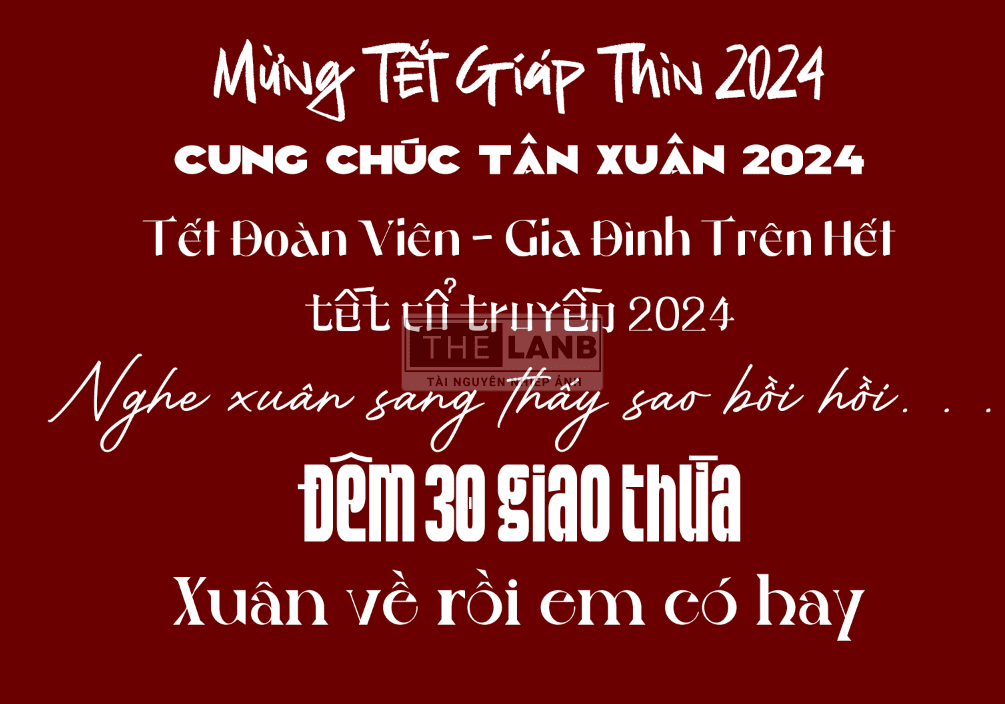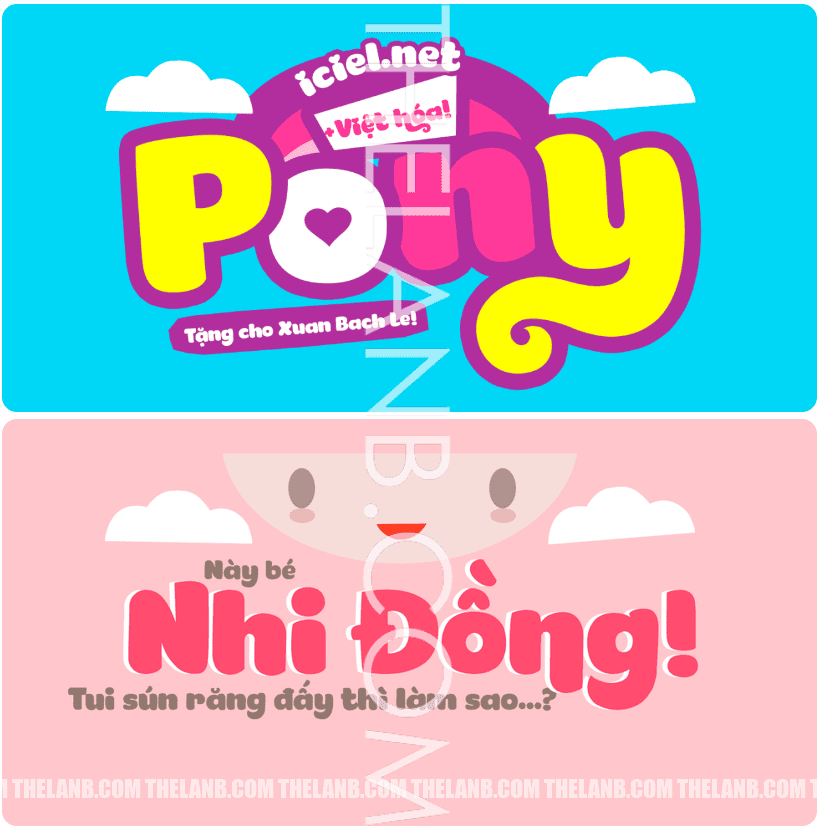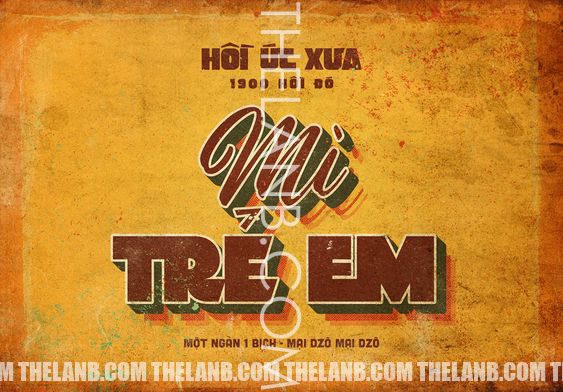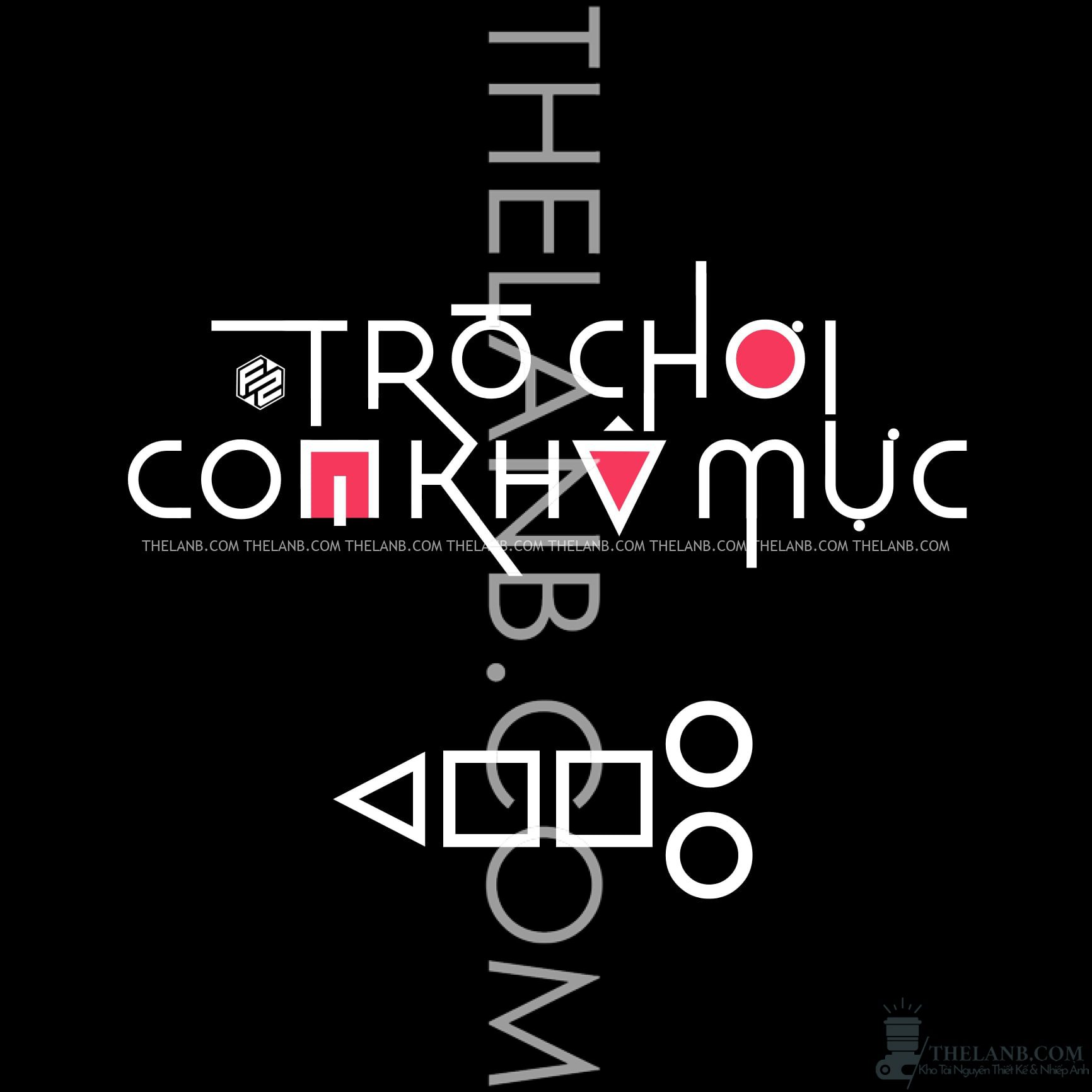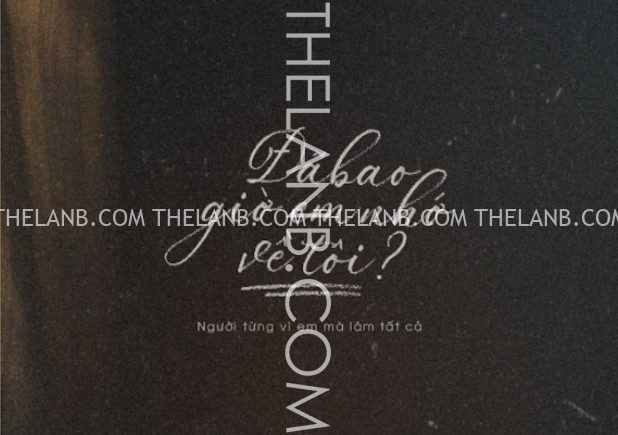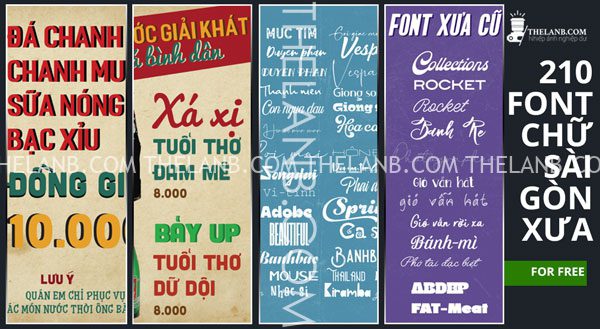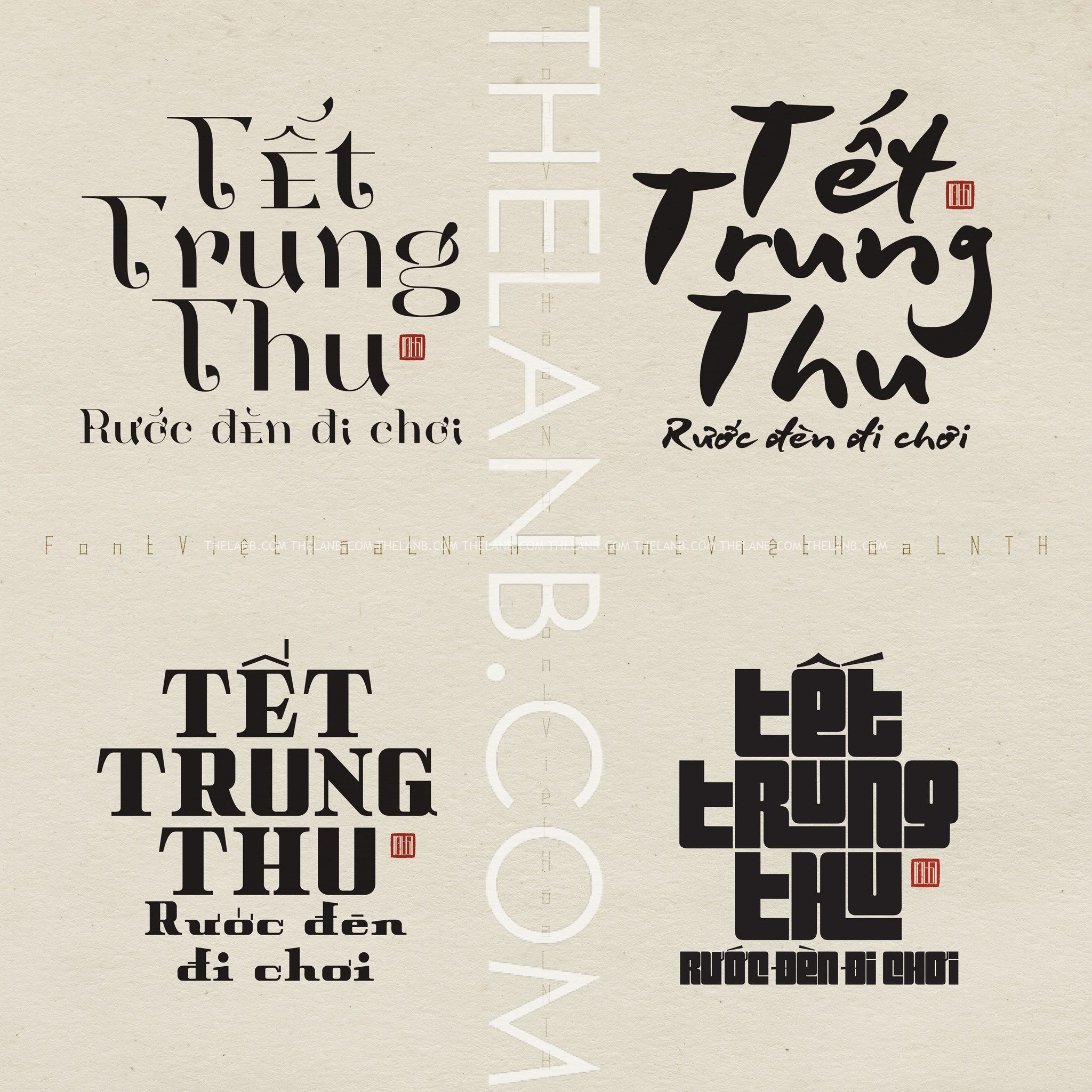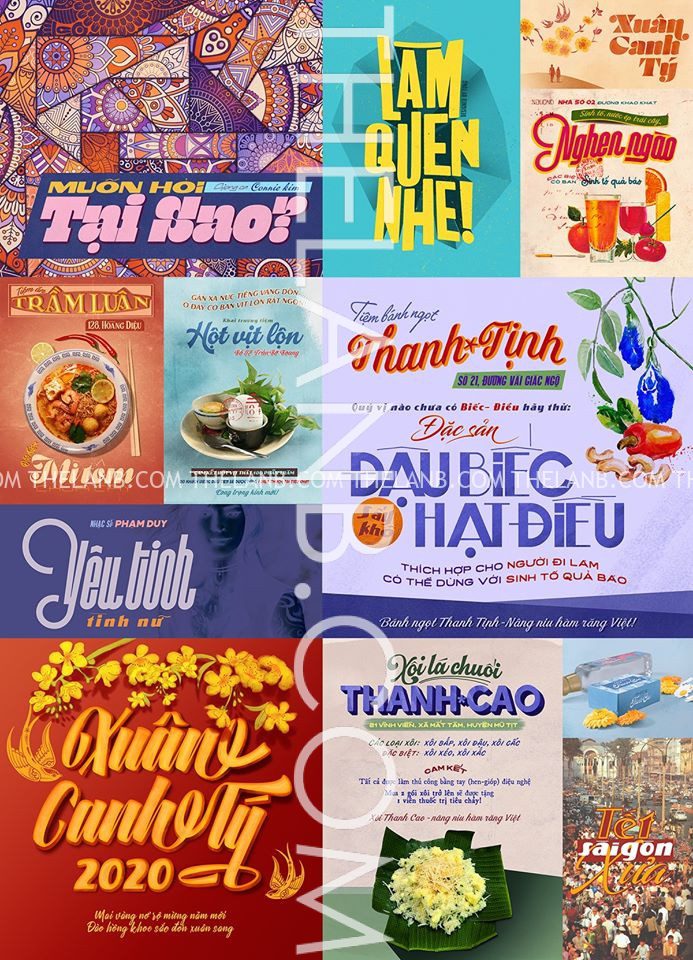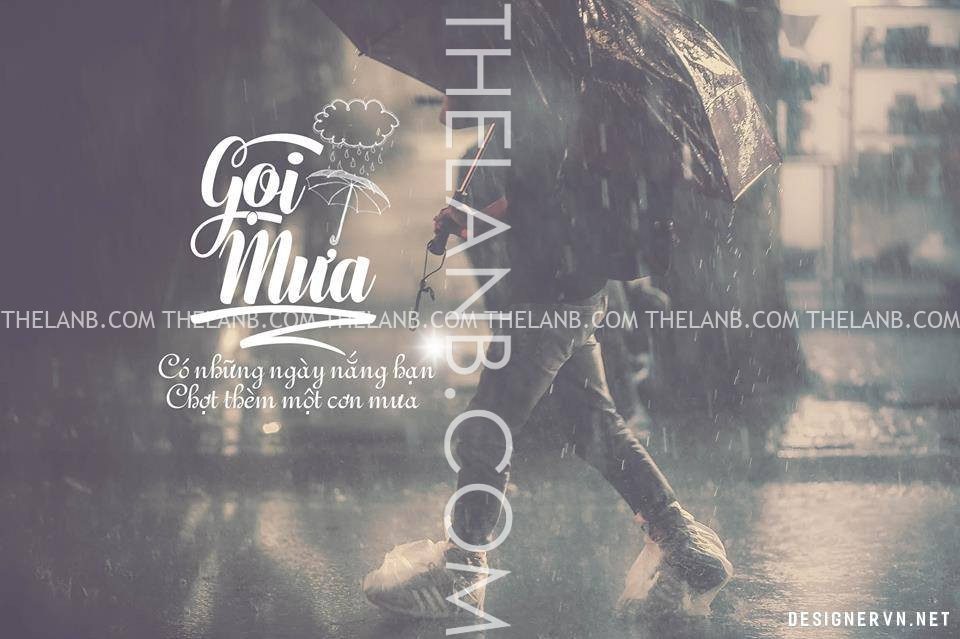
Các font này có đi riêng lẻ hoặc phối hợp với các font dạng script khác đều rất ổn nên bạn có thể thoải mái sáng tạo để thiết kế các ấn phẩm hoặc làm typography như hình demo bên dưới.
Bao gồm 9 kiểu font chữ.